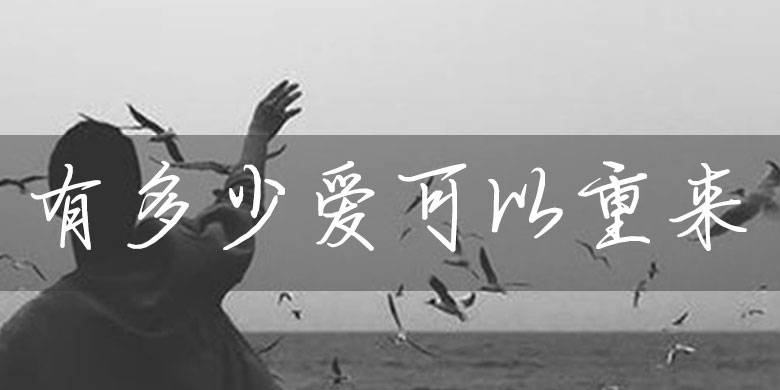
方正手迹-有多少爱可以重来
字体品牌: 方正手迹 设计师:余丹 字体分类:创意书写 字体属性:精品字 字符集:大陆简体(GB2312-80) 发布时间: 2019
粗细变化有致,连笔较多,骨骼清秀俊雅。行笔节奏有徐有急,字笔锋纤细凌厉,点划粗细错落有致。适用于文艺类的书刊、品牌广告和产品包装设计,以及社交网络的个性化用字。